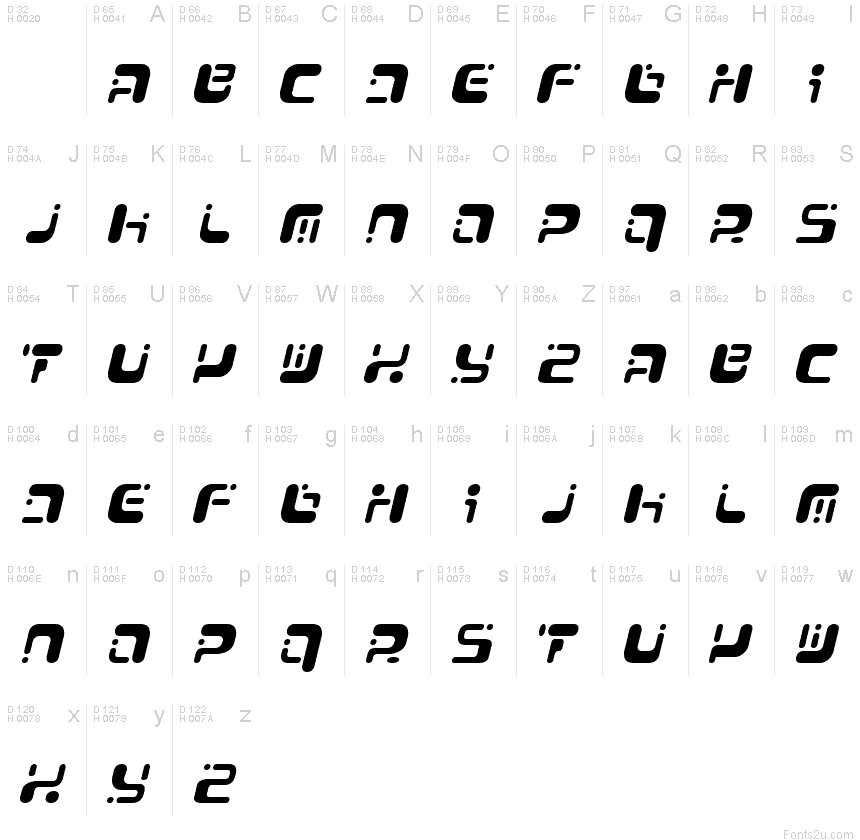
Lastu # 1, progettata da Fenotype, è un carattere display futuristico gratuito costruito con tratti ampi e arrotondati. Le sue giunzioni interrotte e le forme geometriche compatte conferiscono alle lettere l'aspetto di un logo elettronico personalizzato.
Un poster per un evento tecnologico è la sua ambientazione più evidente, e le forme segmentate si adattano anche alla grafica di giochi e al packaging musicale. Nel merchandising e nel branding digitale, la stessa costruzione intagliata collega le lettere alle icone di interfaccia e alla grafica hardware aerodinamica.